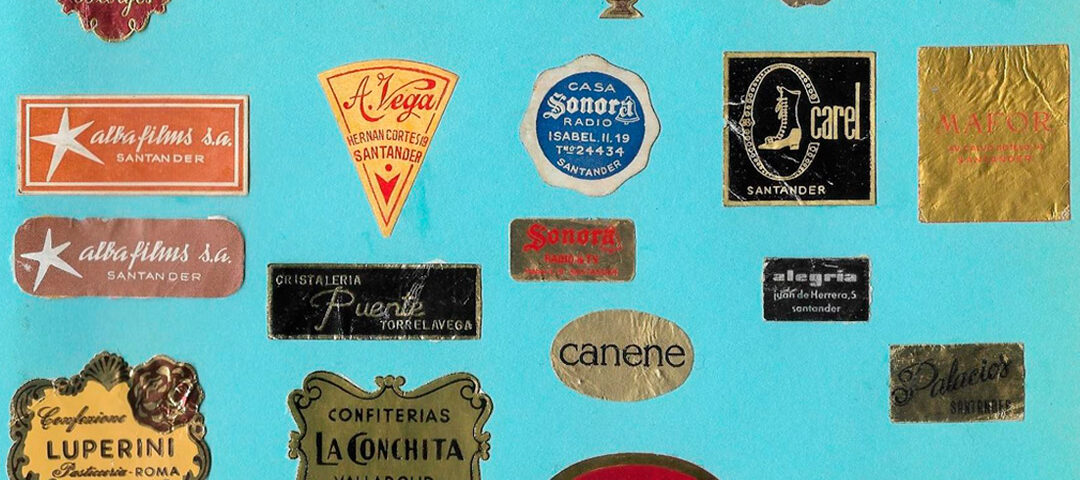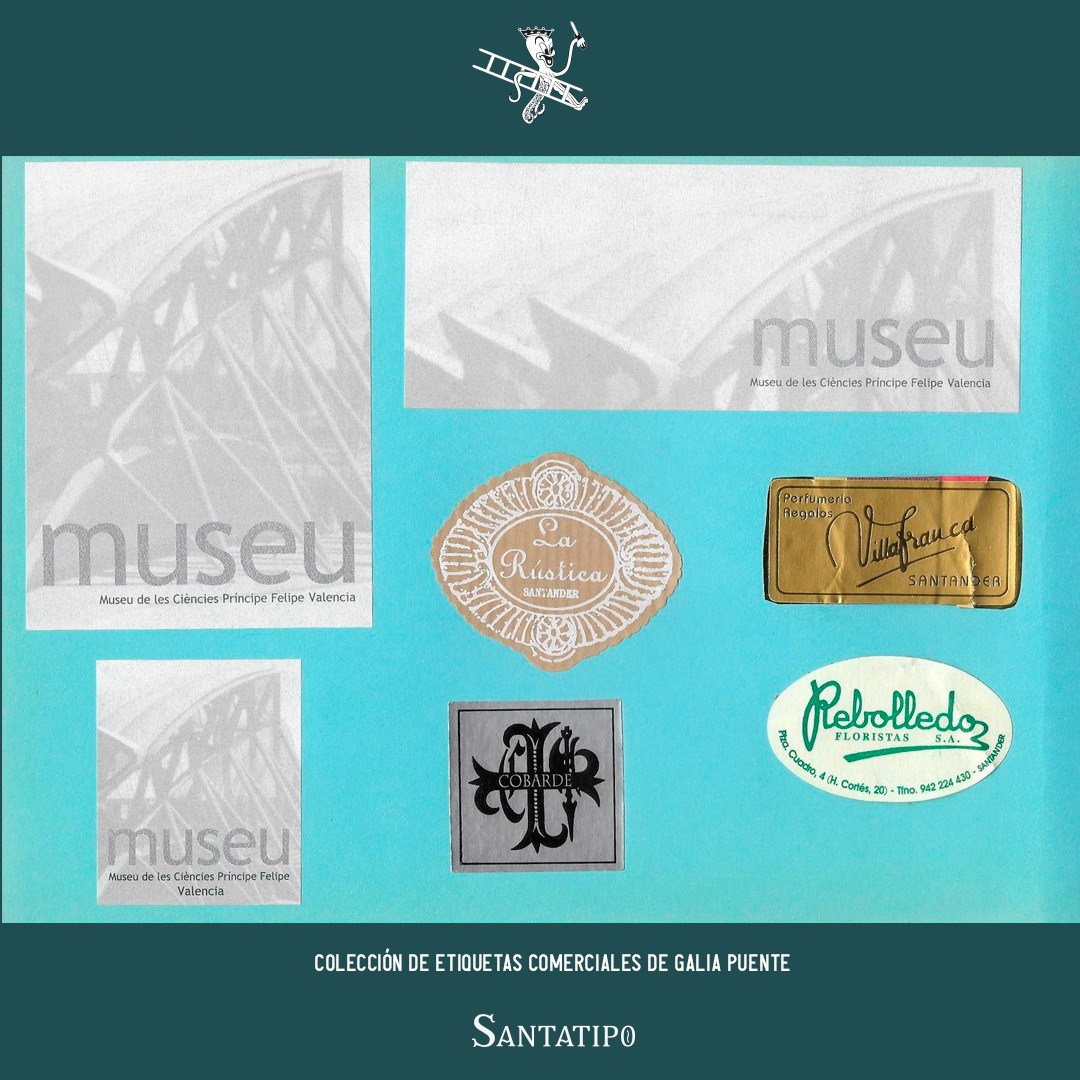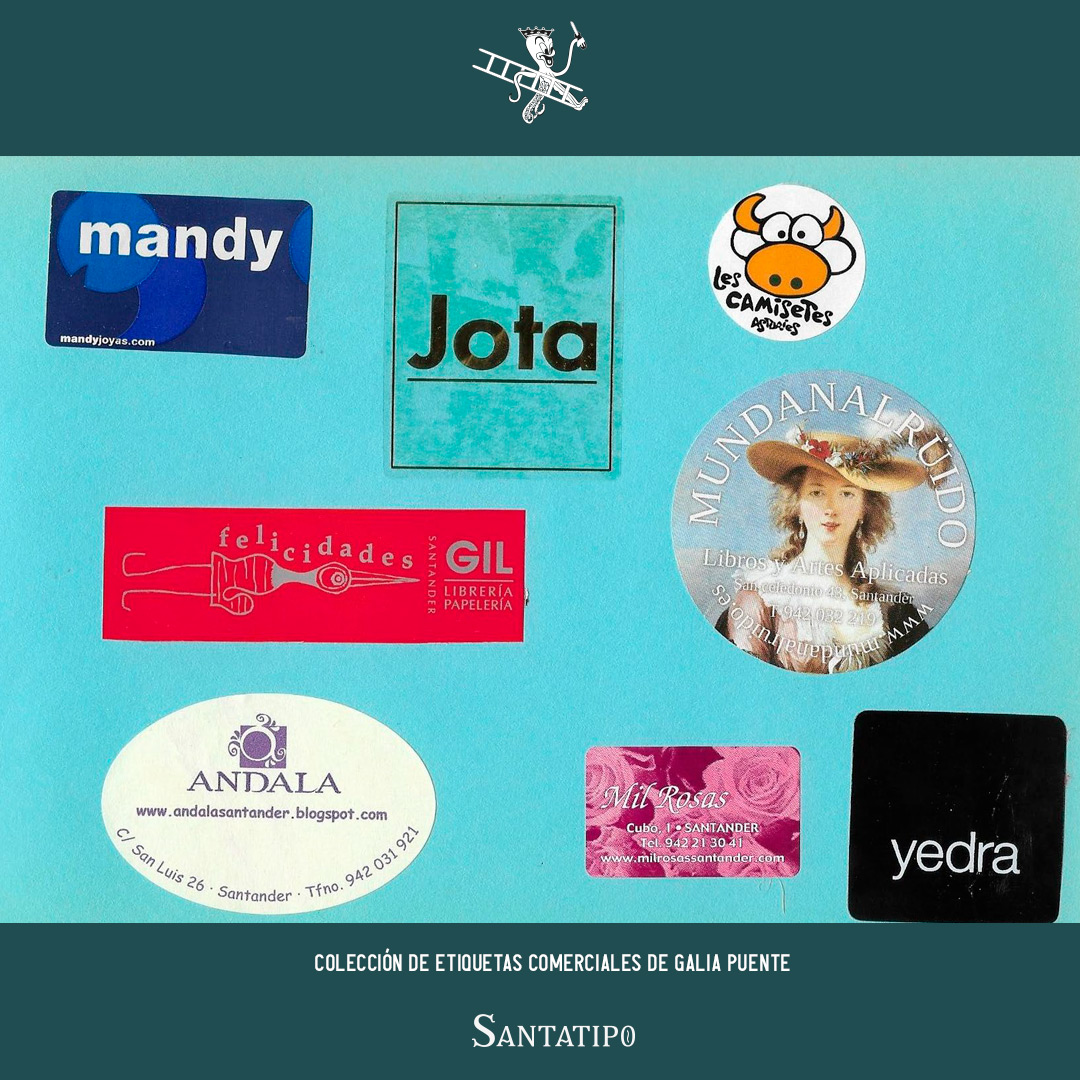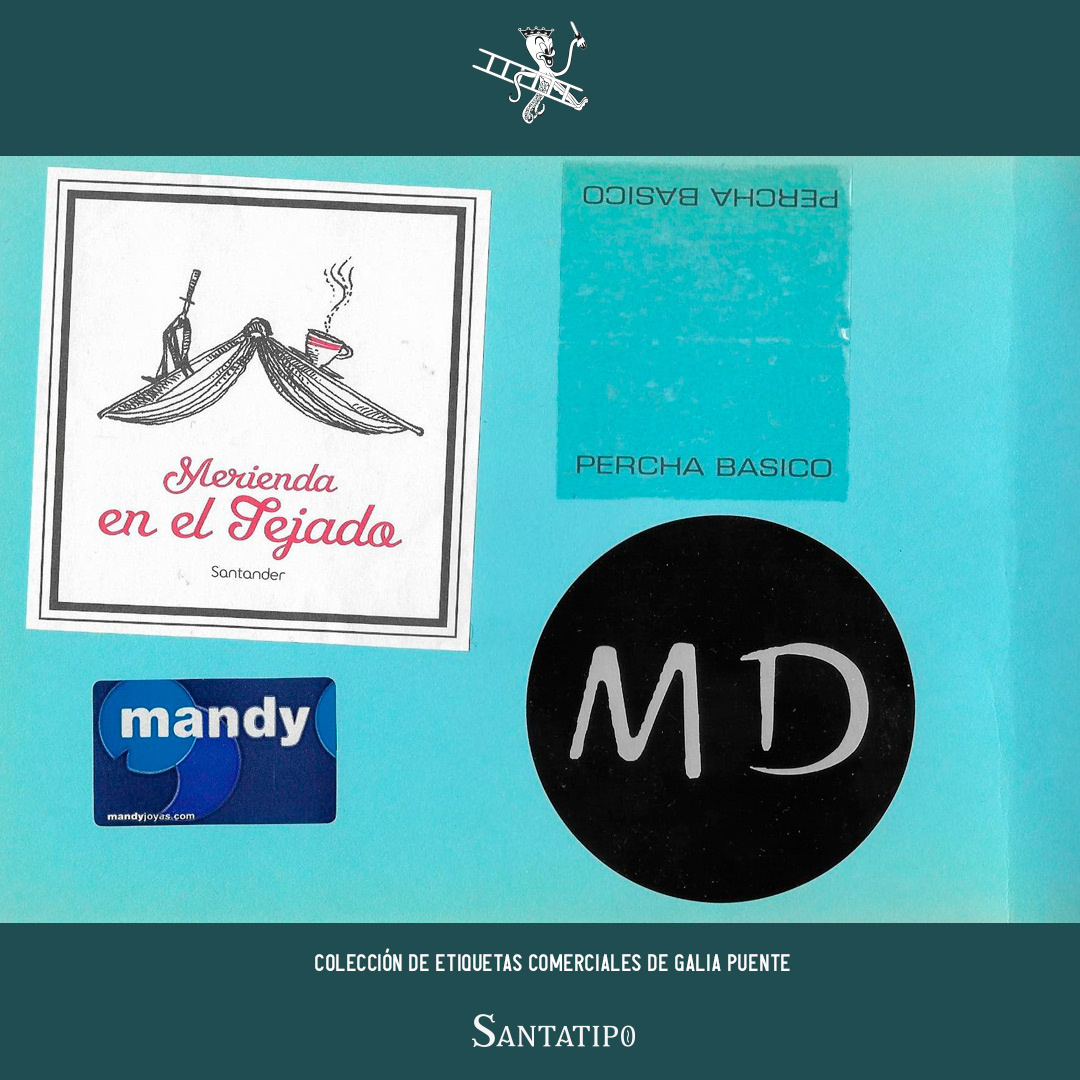
Colección de Etiquetas Comerciales
Hace fuimos publicando esta colección de etiquetas en nuestras redes sociales. Pertenecen a la colección personal de Galia Puente. Son una serie de etiquetas que lleva recopilando en los últimos años de diversos comercios, mayoritariamente de Santander, pero encontramos también de otras Ciudades españolas y europeas.
Os dejamos este archivo gráfico y tipográfico maravilloso para vuestro disfrute.
Colección de etiquetas de Galia Puente. Cedidas para Santatipo.